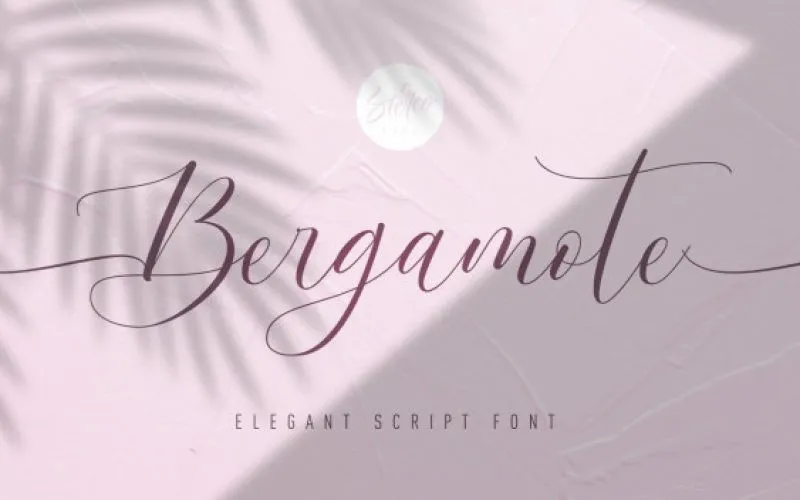
A Bergamote Font é uma nova seleção para designers que procuram adicionar personalidade aos seus trabalhos digitais. Esta fonte de escrita gótica oferece opções incríveis para diversos usos, desde a criação de logomarcas até os títulos de livros e filmes. Além disso, ela é uma ótima escolha para destacar frases curtas ou longas em letras secundárias quando combinada com fontes serifadas ou gerais. Hamilton, o designer desta fonte, trouxe uma dose de criatividade ao oferecer ligaturas personalizadas que permitem uma experiência única e memorável para qualquer projeto. Para aqueles interessados em explorar novas maneiras de expressar suas ideias digitais, a Bergamote é uma ótima escolha. Experimente Cholasette para complementar seu trabalho!